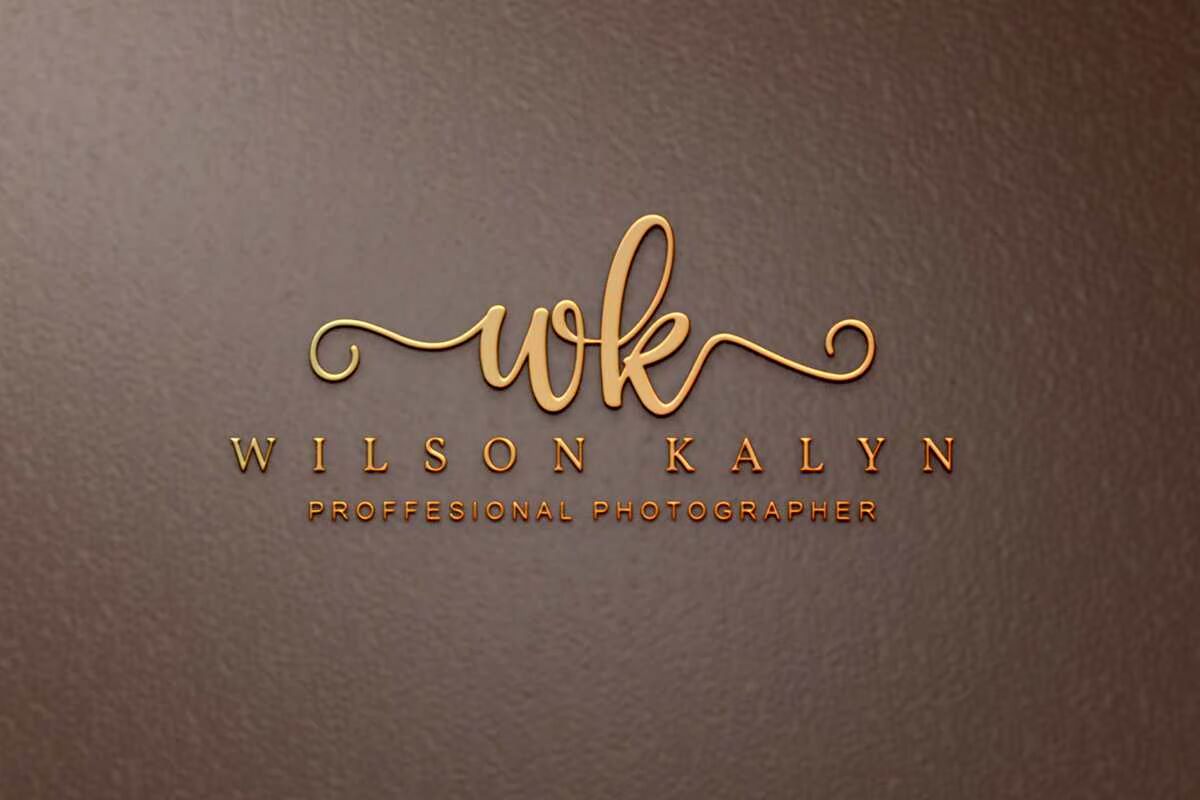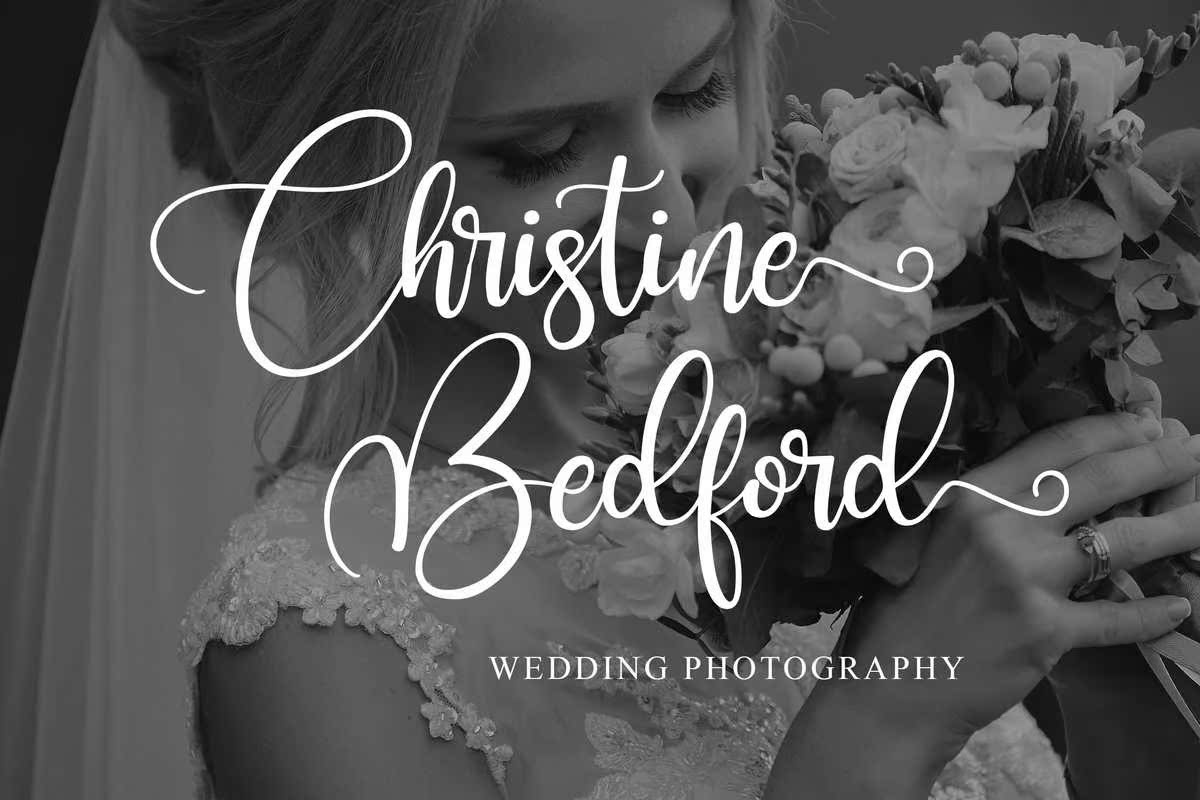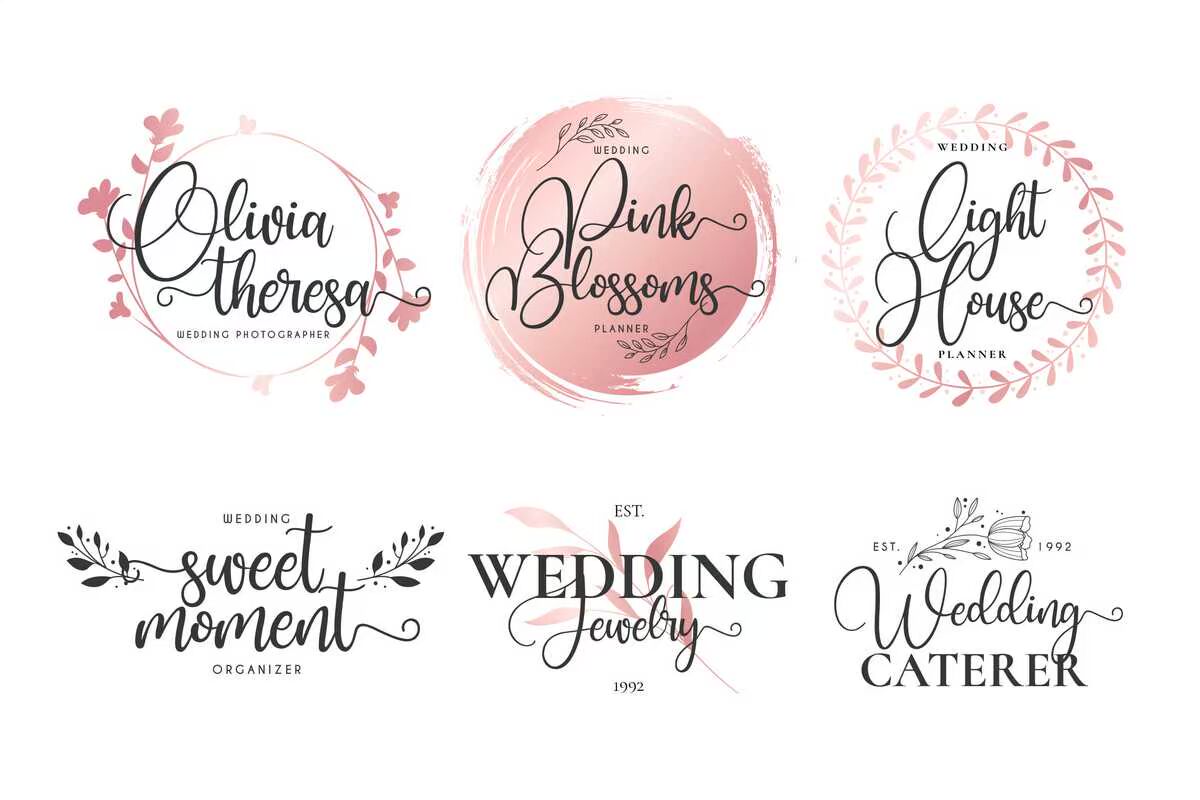
HIMELLATIII是一个美丽而可爱的脚本,适用于品牌推广、婚礼庆典和其他浪漫项目。此字体的编码意味着您可以访问符号和SWASHEASE!所有小写字母,包括开始和Swashes。HimallaiiiiiI是一个美丽的、可爱的文字,适用于品牌推广、婚礼和其他浪漫项目。此字体的编码意味着您可以访问符号和Swashease!所有小写字母都包含开始和结束标记。